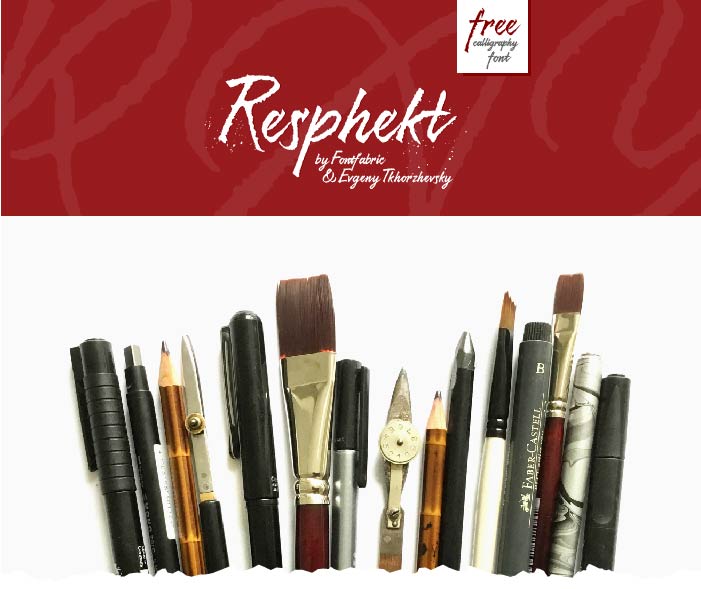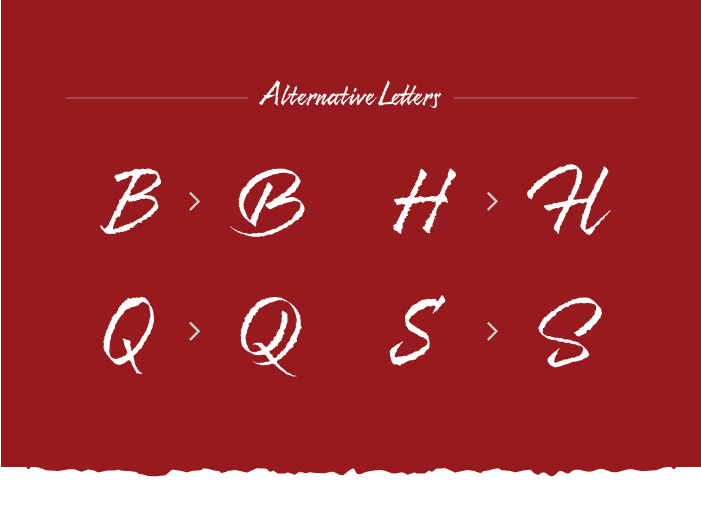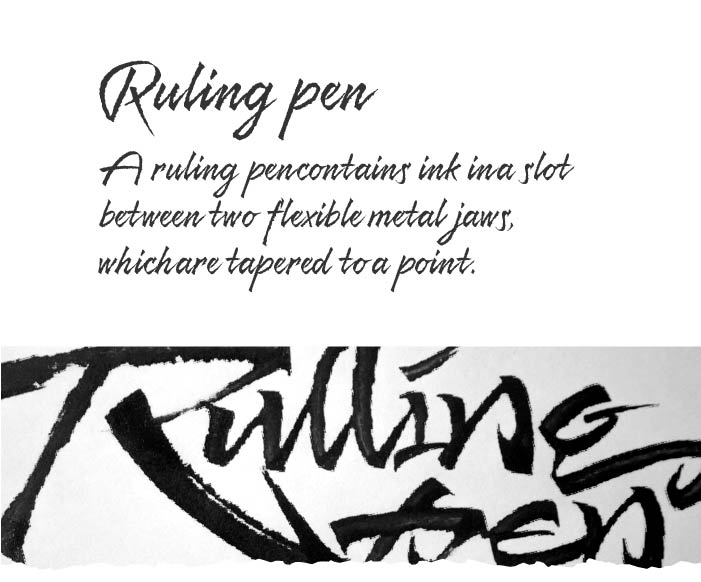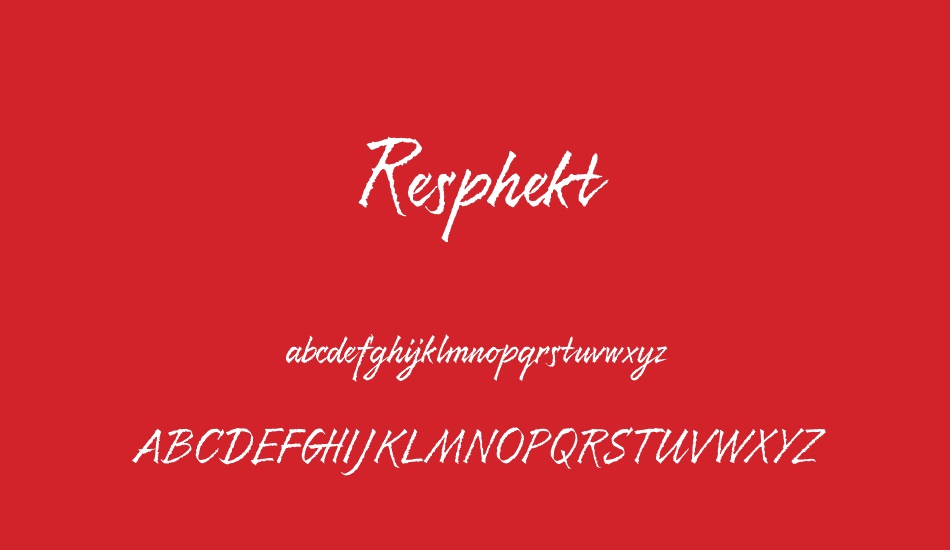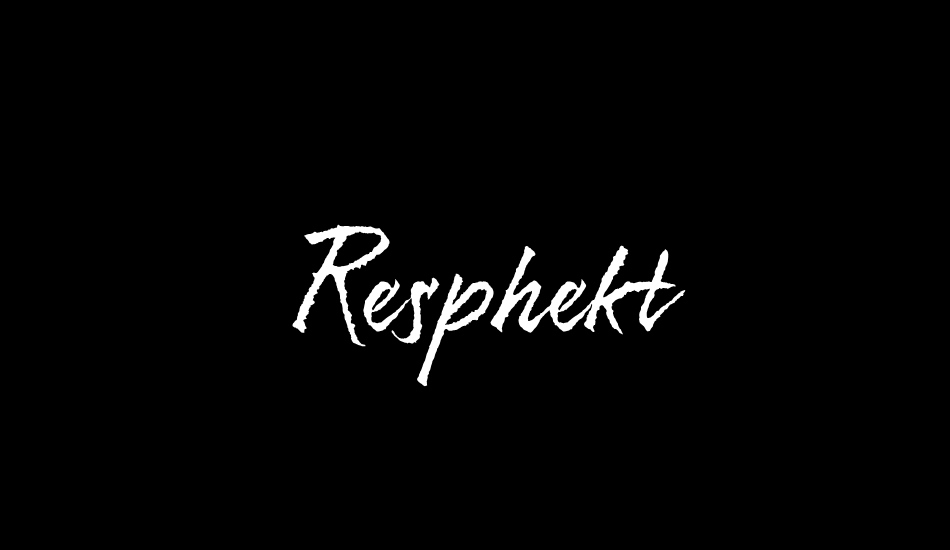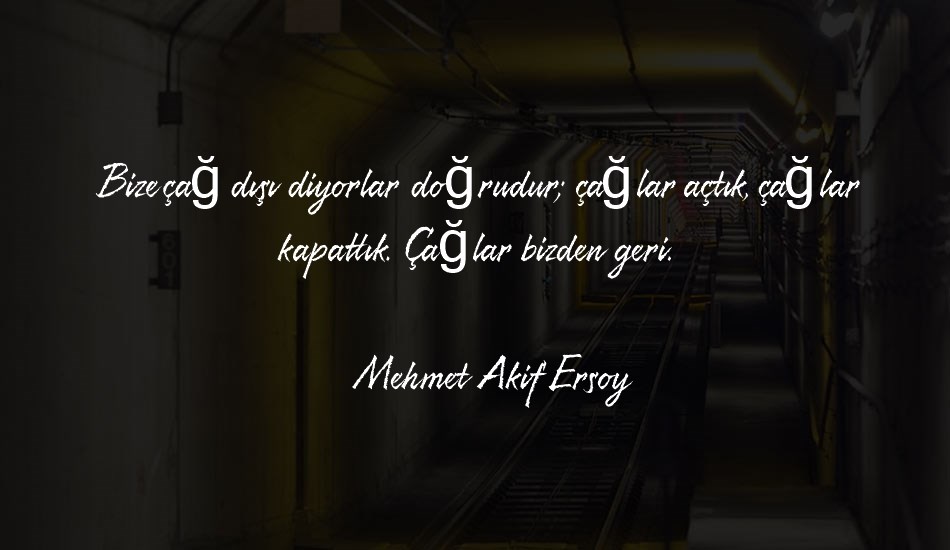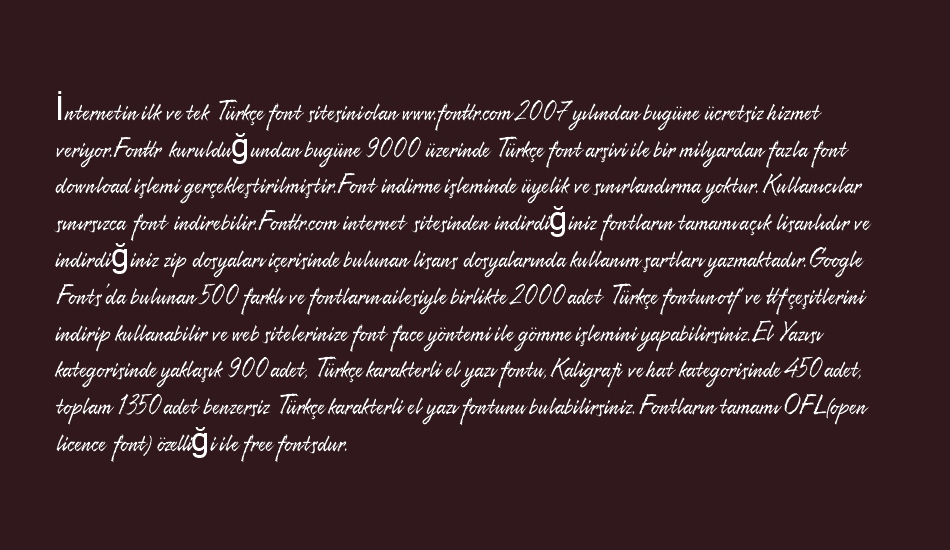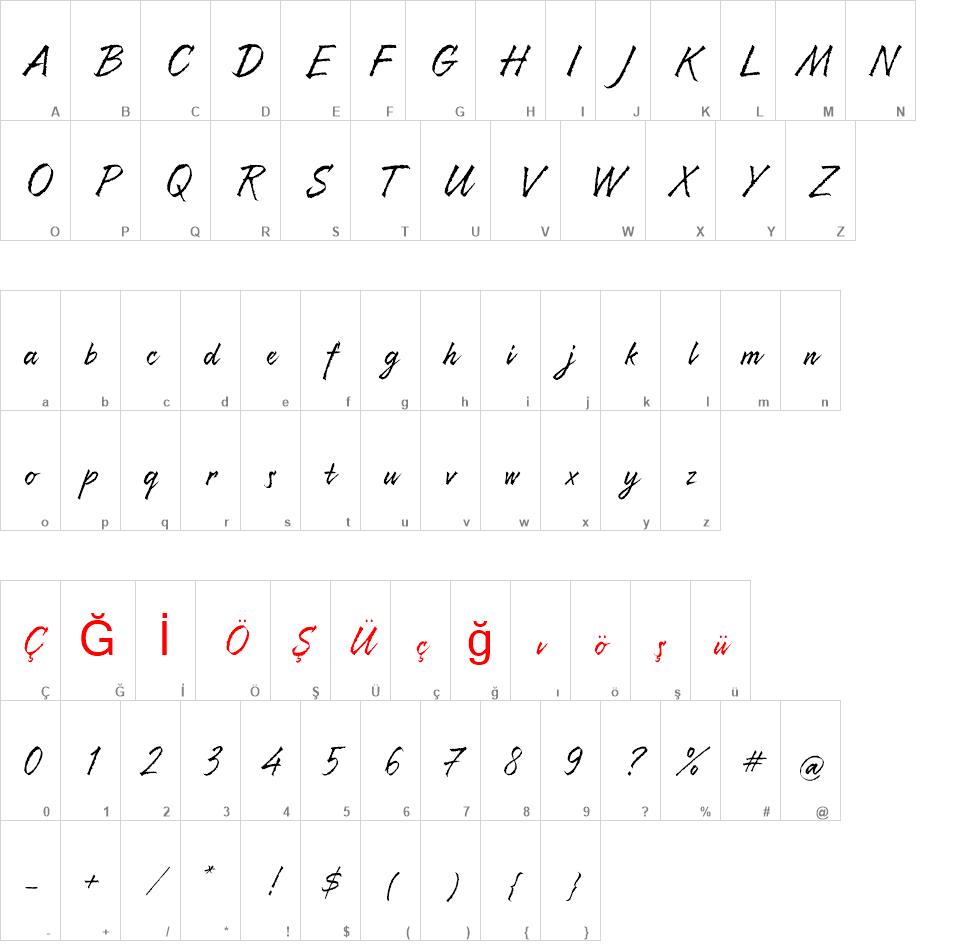
Rus tipi çizim makinesi - Evgeny Tkhorzhevsky tarafından Fontfabric için özel olarak tasarlandı.
Resphekt, yazarın ya da yazarın görebileceği kadarıyla el yazısını taklit eden hafif desenli bir senaryo olup, çünkü Resphekt'in belirgin bir eski okula sahip olduğu söylenebilir. Kesin hatları ve açısal terminalleri sayfanın üzerine çizilmişmiş gibi geliyor. Bu yazıtipi hakkında eski moda bir dolma kalemi - yöneten kalem ya da belki de tüy ve mürekkep püskürmesi - gibi farklı bir anlamı var. Resphekt kesinlikle ekran metni içindir. Şiş şişesi etiketi veya tarihsel bir olay gibi, yaşla oluşturulan belirli bir ilgiyi iletmek istediğinizde idealdir.